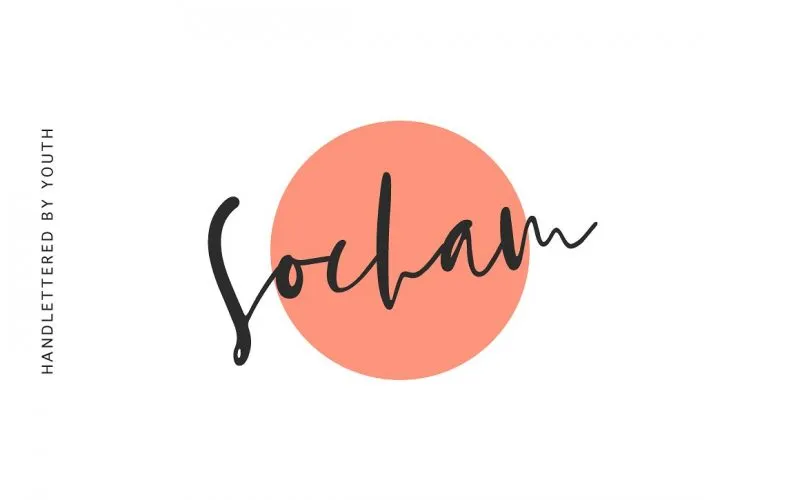
Socham Script Font – Fonte Grátis
Socham Script Font
Bem-vindos! Estamos muito felizes por ter você aqui hoje. Hoje falaremos sobre uma nova adição à nossa gama de fonts modernas: Socham Script Font, criada pelo designer Hamilton. Essa font é baseada no estilo da escrita a mão real e transmite um charme elegante ao seu projeto. Não se engane em pensar que Socham é apenas mais uma opção na gama de scripts digitais; ela traz muitas alternativas estilizadas para dar vida à sua criação, tornando-a única e especial. Perfeito tanto para projetos pessoais, como para iniciativas comerciais. Seja você que deseja criar cartões de noiva bonitos ou frisas encantadoras para a sua casa, Socham é ideal para isso. Além disso, ela também será ótima para o seu negócio pequeno, capas de livros, papelaria e até mesmo publicações como revistas. Tudo isso sem esquecer dos seus projetos pessoais, seja uma carta personalizada ou um design gráfico único que você tem em mente. Socham Script Font é a escolha perfeita para qualquer projeto onde o estilo deve ser valorizado.